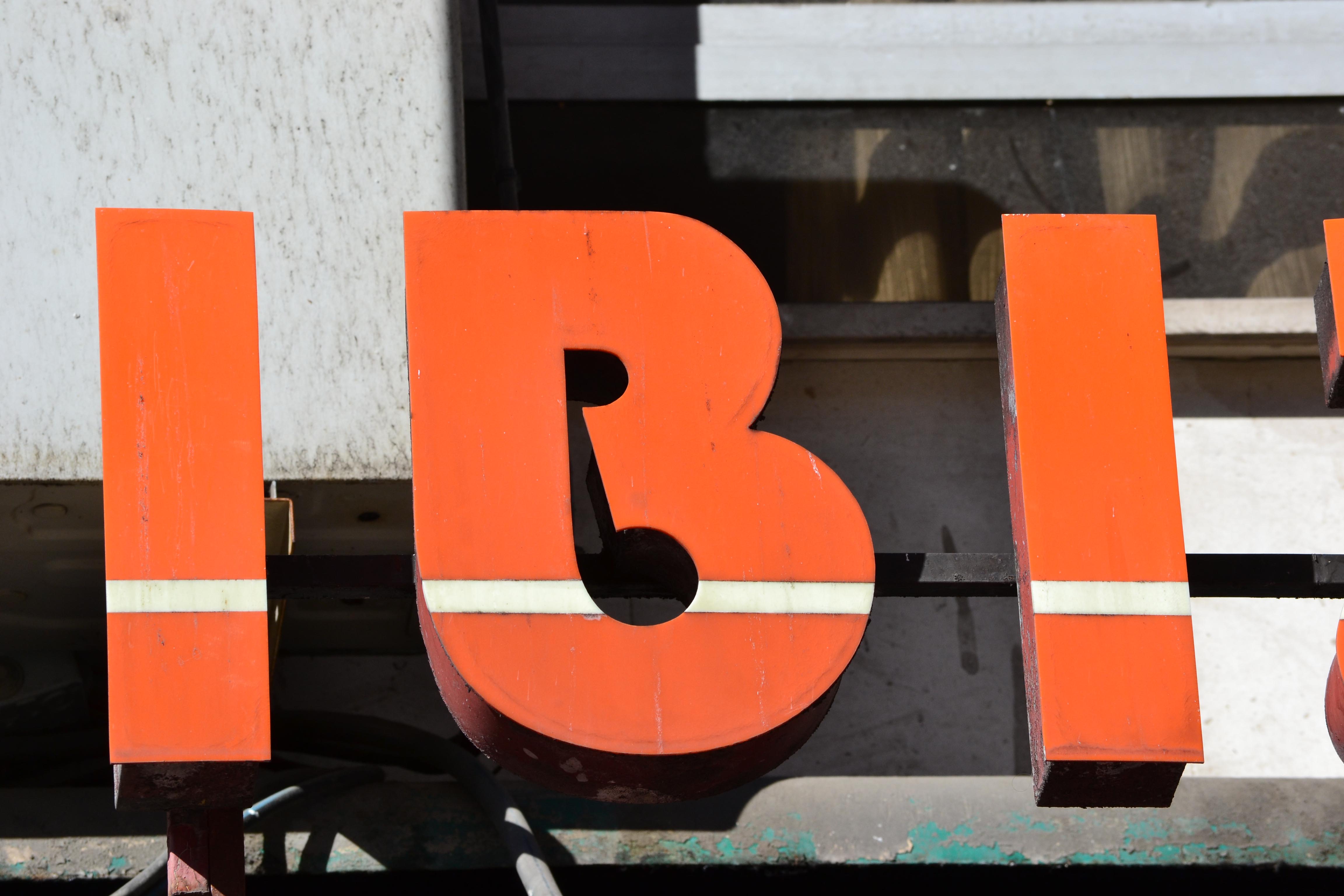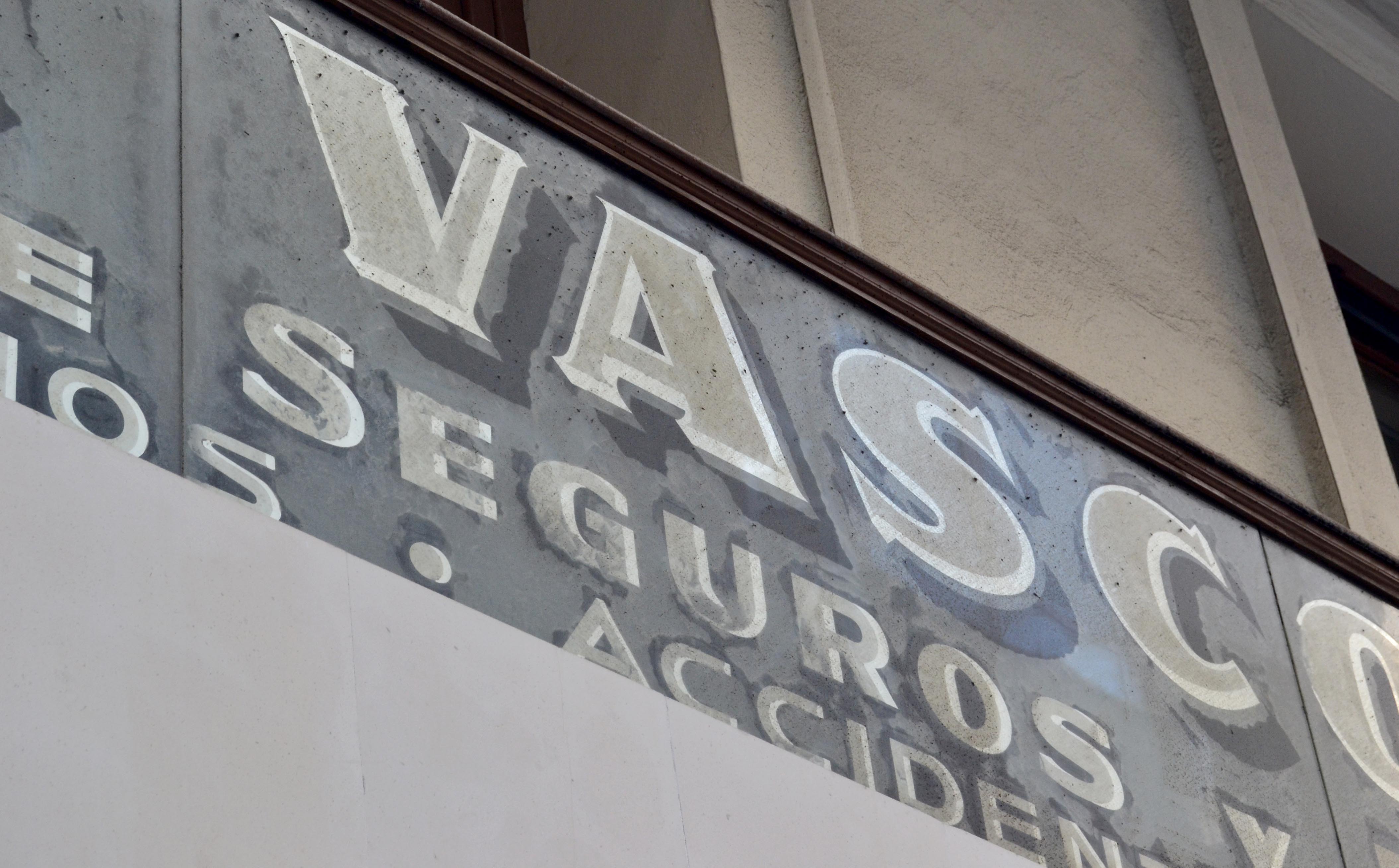
Guardianes del Patrimonio Gráfico de Cantabria
¿Qué es el
Patrimonio gráfico?
El patrimonio gráfico de una ciudad se refiere a la colección visual de elementos que representan la historia, la cultura y la identidad de esa ciudad a lo largo del tiempo.
Este término abarca una variedad de elementos visuales, desde edificios icónicos y monumentos hasta carteles, anuncios, obras de arte urbano, señales históricas y otros elementos visuales que contribuyen a la identidad gráfica de la ciudad.
El patrimonio gráfico es esencialmente la suma de todas las imágenes, gráficos y diseños que se han utilizado en la ciudad a lo largo de su historia para comunicar mensajes, conmemorar eventos, representar valores culturales y transmitir la esencia de la ciudad a residentes y visitantes.
Letreros y anuncios que han estado presentes en la ciudad durante mucho tiempo y que se han convertido en parte integral de la imagen urbana.
Diseño de carteles y folletos: Elementos impresos utilizados para eventos, promociones y comunicaciones en la ciudad a lo largo del tiempo.
Símbolos y logotipos que son reconocidos y asociados con la ciudad, como escudos heráldicos, banderas y otros emblemas.
En conjunto, el patrimonio gráfico de una ciudad refleja su historia, valores culturales y visión de futuro, y desempeña un papel importante en la identidad y la relación emocional que los habitantes tienen con su entorno urbano.
Guardianes del
patrimonio gráfico
de Cantabria
Somos una Asociación cultural que tiene como objetivo principal, preservar el Patrimonio gráfico y visual de Cantabria. Para ello tratamos de poner en valor las muestras que se encuentran a día de hoy en las calles, concienciando a comercios, ciudadanos e instituciones que debemos conservar estos objetos, que generan memoria colectiva que trasciende de Patrimonio Visual y Gráfico de nuestras ciudades y que ayuda a conocer la historia de la ciudad desde otro punto de vista: el de sus calles y comercios. Dentro la preservación, con nuestro pocos medios y gracias a ciudadanos, comerciantes y seguidores de la Asociación, hemos rescatado y guardado más de 60 Carteles y material gráfico de Negocios abandonados o negocios cerrados. Todas estas acciones nos ayudan a divulgar en redes sociales y prensa el trabajo de la asociación y el amplio patrimonio gráfico que tenemos en Cantabria. Con todo ello, en 2020 pudimos editar el libro “Santatipo: Memoria tipográfica de los rótulos comerciales de Santander” editado con Libros.com a través de una campaña de crowdfounding, con el apoyo del Ayuntamiento de Santander. Además, Santatipo es miembro fundador la “Red Ibérica de Defensa del Patrimonio Gráfico“ una red que engloba más de 50 proyectos similares al nuestro. La asociación y sus actividades siguen creciendo, pero necesitamos toda la ayuda posible.